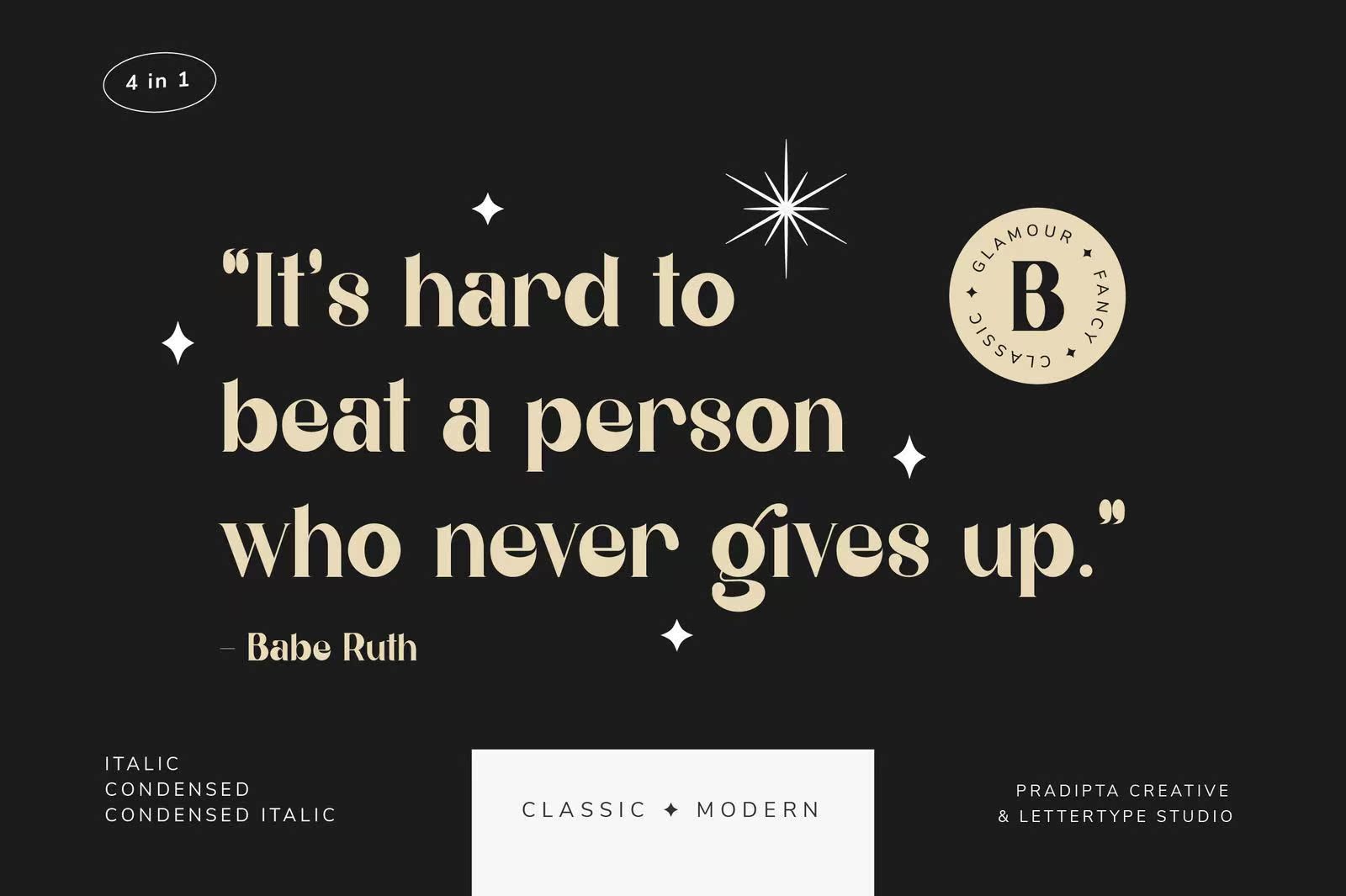
BelgiaSerifisaclassic,GlamurandFancyFont。这款Font将在标志设计、品牌推广、服装、标牌、海报、婚礼宣传等方面完美无瑕!我创建此字体的目标是创建一个模型和经典样式的示例,这将有助于您的项目删除和删除。不要错过!BelgiaSerifisaclassic,GlamurandFancyFont。这款Font将在标志设计、品牌推广、服装、标牌、海报、婚礼宣传等方面完美无瑕!我创建此字体的目标是创建一个模型和经典样式的示例,这将有助于您的项目删除和删除。不要错过!